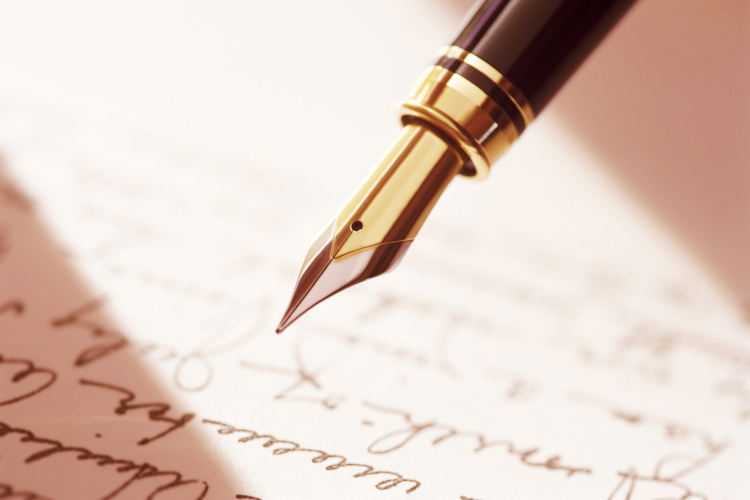
Was sind geschwungene Schriftarten?
Geschwungene Schriftarten, auch bekannt als Skript-Schriften oder Schreibschriften, sind Schriftarten, die sich durch ihre fließenden, oft eleganten Buchstabenformen auszeichnen. Diese Schriftarten sind von der handschriftlichen oder kalligrafischen Schreibweise inspiriert, wobei die Buchstaben meist durch feine Linien miteinander verbunden sind. Es gibt jedoch auch Varianten, die auf die Verbindung verzichten und stattdessen einen loseren Stil beibehalten. Sie reichen von klassischen und formellen Designs, die an historische Kalligrafie erinnern, bis hin zu modernen, spielerischen und kreativen Varianten.
Ein kurzer Blick in die Geschichte geschwungener Schriftarten
Die Ursprünge geschwungener Schriftarten liegen in der Kalligrafie, einer Kunstform, die Jahrhunderte zurückreicht. Bereits in der Antike wurden geschwungene Linien verwendet, um Texte zu gestalten, sei es auf Papyrus, Pergament oder Stein. Besonders im Mittelalter spielte die kalligrafische Schrift eine zentrale Rolle in Manuskripten, die von Mönchen mit großer Sorgfalt von Hand geschrieben wurden.
Im 17. und 18. Jahrhundert erreichte die Kalligrafie ihren Höhepunkt, als elegante, geschwungene Schriften wie die Copperplate entwickelt wurden. Diese Schriftart, die ursprünglich mit Feder und Tinte geschrieben wurde, diente als Vorlage für viele moderne geschwungene Schriftarten. Mit der Erfindung des Buchdrucks und später der Typografie wurden kalligrafische Stile in Druckschriften umgesetzt, um dieselbe Eleganz und Anmut auf gedruckten Seiten zu bewahren.
Im digitalen Zeitalter erlebten geschwungene Schriftarten eine Renaissance, da moderne Designsoftware einfacher denn je macht, individuelle Schriftarten zu gestalten und anzupassen. Heute finden Sie diese Schriftarten überall: Von Drucksachen über Webseiten und Produkte bis hin zu Tattoos.
Einige der bekanntesten Designs mit geschwungenen Schriftarten zeigen, wie vielseitig diese Schriftarten sein können. Das Logo von Coca-Cola ist ein Paradebeispiel für den zeitlosen Charme dieser Schriften. Auch die Marke Ladurée, bekannt für ihre luxuriösen Macarons, nutzt eine elegante, kalligrafische Schrift, um Exklusivität und Stil zu vermitteln.
Wie nennt man geschwungene Schriften?
Geschwungene Schriften werden häufig als Schreibschrift, Kalligrafie-Schriftarten oder Skript-Schriften bezeichnet. In der Welt des Designs sind sie auch unter Begriffen wie Cursive Fonts, Handwriting Fonts oder Brush Script bekannt. Diese Begriffe verdeutlichen die handschriftliche oder kalligrafische Natur der Schriften.
Warum sind geschwungene Schriftarten so beliebt?
Die Popularität geschwungener Schriftarten lässt sich auf mehrere Faktoren zurückführen:
- Emotionale Verbindung: Geschwungene Schriften vermitteln oft ein Gefühl von Wärme, Nostalgie und Persönlichkeit. Sie erinnern an handgeschriebene Briefe und verleihen Designs eine menschliche Note.
- Eleganz und Luxus: Viele geschwungene Schriftarten strahlen eine zeitlose Eleganz aus. Sie werden häufig in hochwertigen Branding-Projekten oder besonderen Anlässen wie Hochzeiten, Jubiläen und Festen verwendet.
- Flexibilität: Ob verspielt, modern oder klassisch – geschwungene Schriften können sich an verschiedenste Stile anpassen und sind daher unglaublich vielseitig.
- Unverwechselbarkeit: In einer Welt, die von Sans-Serif-Schriften wie Arial und Helvetica dominiert wird, bieten geschwungene Schriftarten eine willkommene Abwechslung und lassen Designs aus der Masse hervorstechen.
Die Vielseitigkeit geschwungener Schriftarten
Geschwungene Schriftarten sind in nahezu allen kreativen Projekten einsetzbar. Hier einige der häufigsten Anwendungen:
- Einladungen und Grußkarten: Ob Hochzeitseinladungen oder Geburtstagskarten – geschwungene Schriftarten verleihen jedem Anlass eine persönliche und elegante Note.
- Logos und Branding: Viele Luxusmarken setzen auf geschwungene Schriftarten, um Exklusivität zu betonen. Bekannte Beispiele sind die Logos von Cartier oder Coca-Cola.
- Webdesign: Sie eignen sich hervorragend, um Überschriften oder Zitate auf Webseiten hervorzuheben, besonders bei kreativen und künstlerischen Themen.
- Tattoos: Für Namen, Zitate oder Symbole sind geschwungene Schriftarten eine der beliebtesten Wahlen.
- Social Media: Auf Plattformen wie Instagram werden häufig geschwungene Schriften verwendet, um Beiträge und Stories ästhetisch aufzuwerten.
Dank ihrer Flexibilität können geschwungene Schriftarten sowohl traditionell als auch modern wirken, was sie zu einem unverzichtbaren Werkzeug für Designer macht.
Welche Schriftart ist geschwungen?
Geschwungene Schriftarten lassen sich grob in folgende Kategorien einteilen:
- Klassische Kalligrafie-Schriften: Diese erinnern an handgeschriebene Manuskripte und sind oft formell und elegant.
Beispiele: Copperplate und Edwardian Script. - Moderne Schreibschriften: Sie sind lockerer und kreativer, oft inspiriert von handschriftlichen Notizen.
Beispiele: Dancing Script und Pacifico. - Verschnörkelte Schriften: Diese sind besonders dekorativ und enthalten oft florale oder ornamentale Elemente.